如何用字体的方式打开宁安如梦?
柚子最近对《宁安如梦》有点上头,刚开始觉得片头曲+念白很有新意,片尾的吟唱也超有感觉,后来是对里面的疯批台词念念不忘,这不正好增加了新的单款商用字体,就拿来适配一下~
首先是百家造字的杜怀健行隶,这款字体非常独特,有一种穿越的古拙之美。
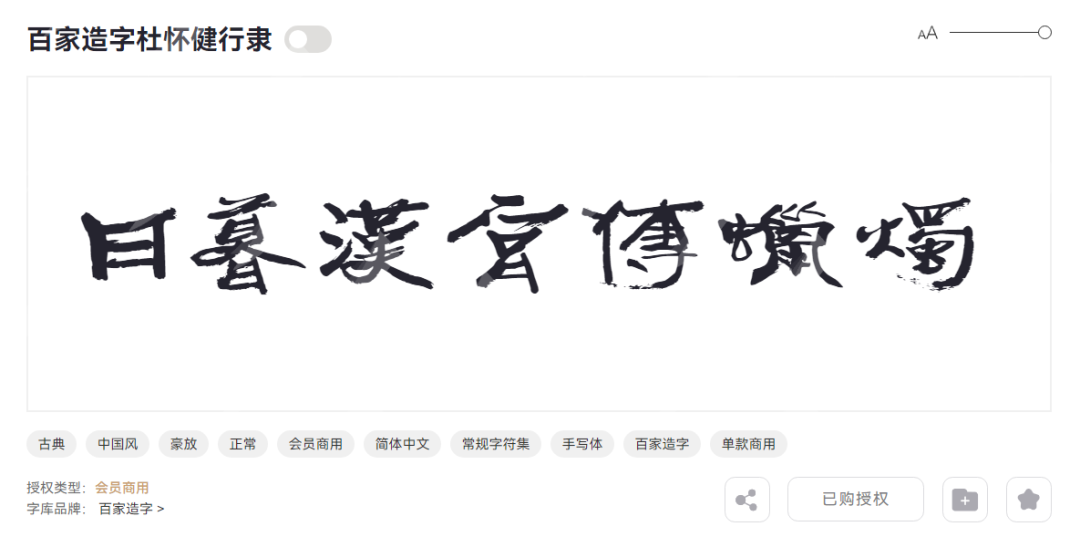
用来匹配《宁安如梦》的海外版海报,顿时宿命感、复杂感都有了。
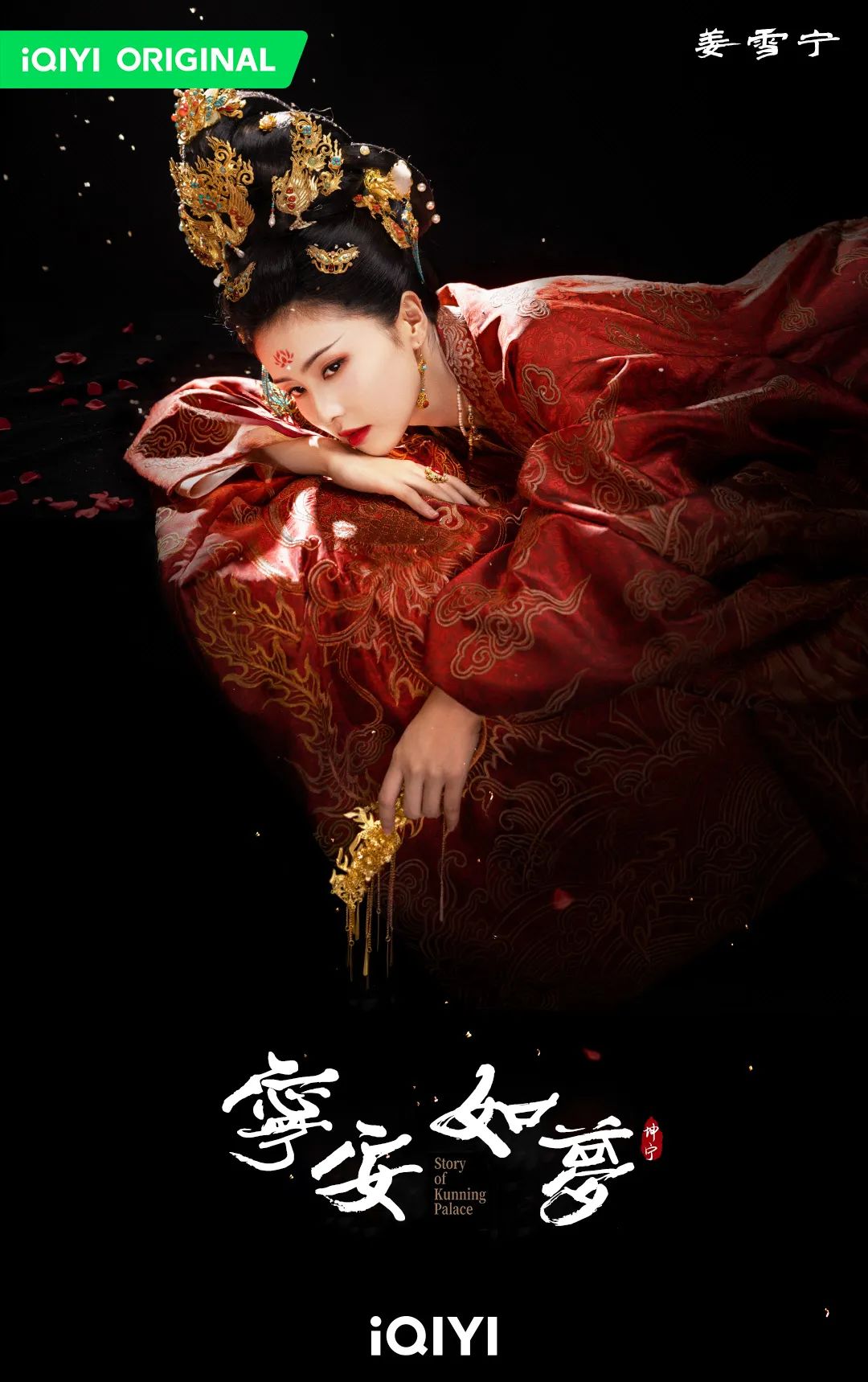
另外一款,百家造字知宥体,也是柚子很喜欢的字体,非常有故事感。
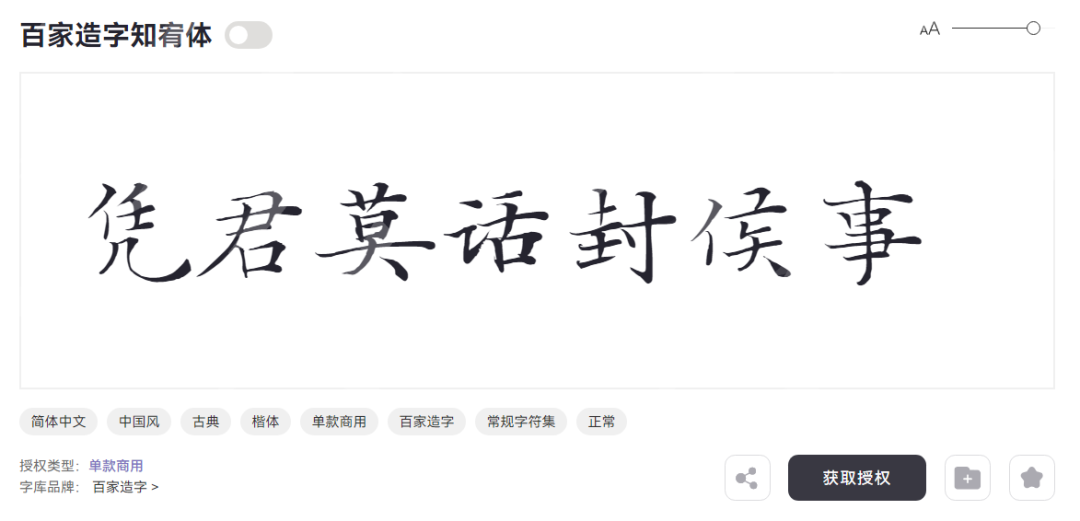
比较适合那句最出圈的台词,“苦果亦是果”,隐忍中又带些强制。
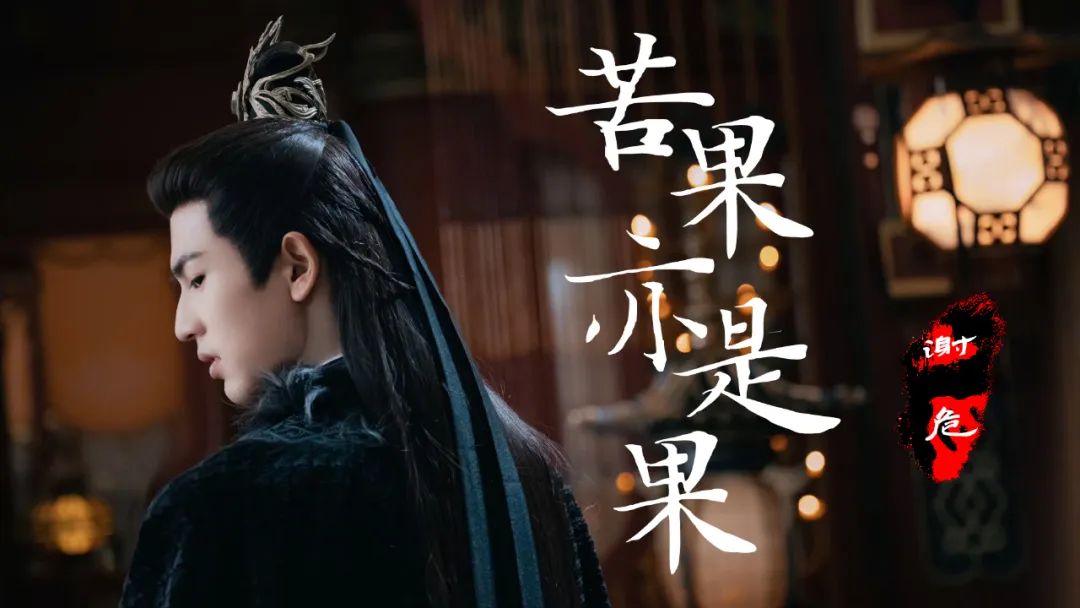
而清丽风雅的百家造字汲古楷书,没有一丝丝攻击性。
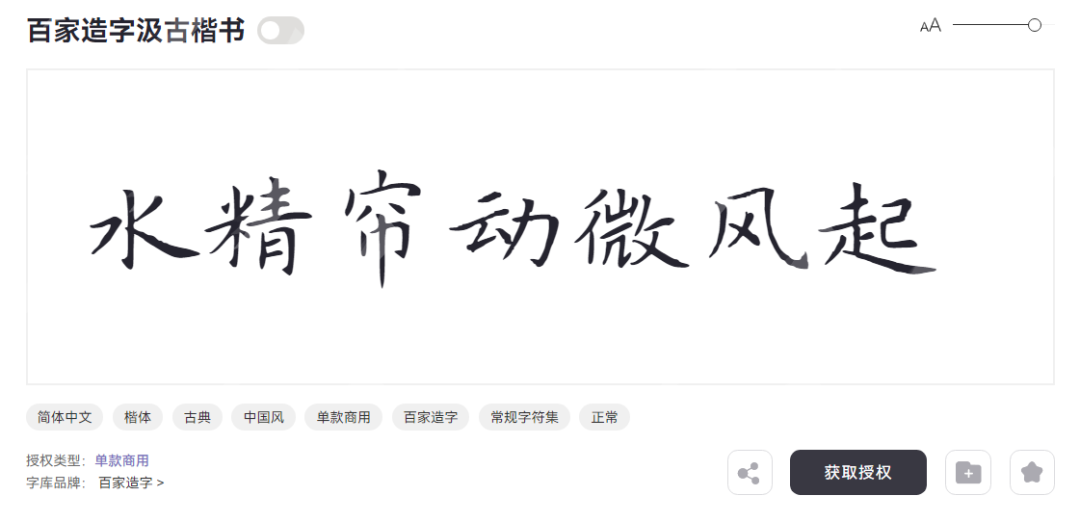
正好书写让“谢某无拘”,让姜雪宁以命换命的白月光——张遮。
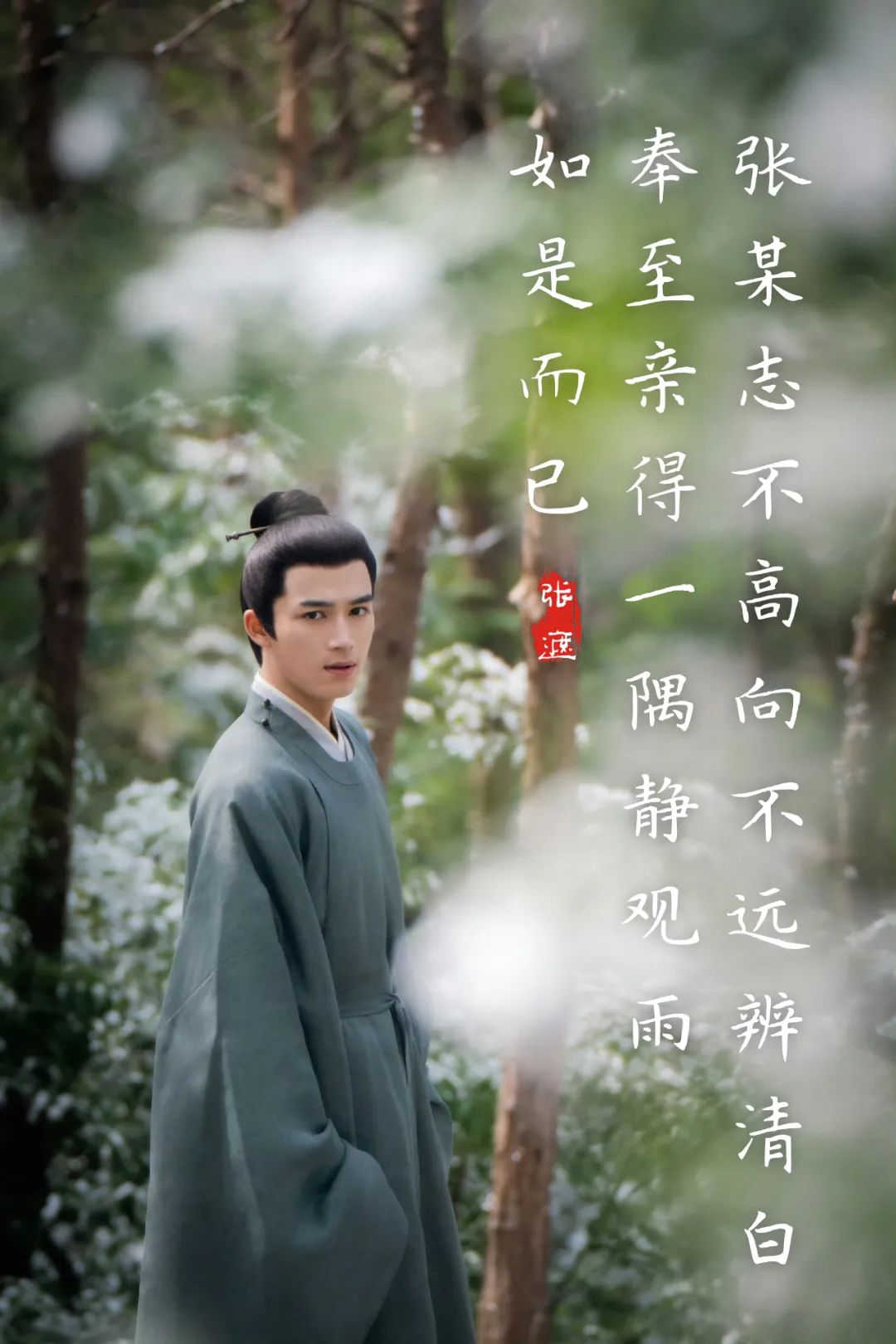
其实《宁安如梦》播到现在,大概可以用一句话来总结,那就是“一座宁安宫,两世荒唐梦”,而我选了百家造字小隶体,来展现女主的宿命论。
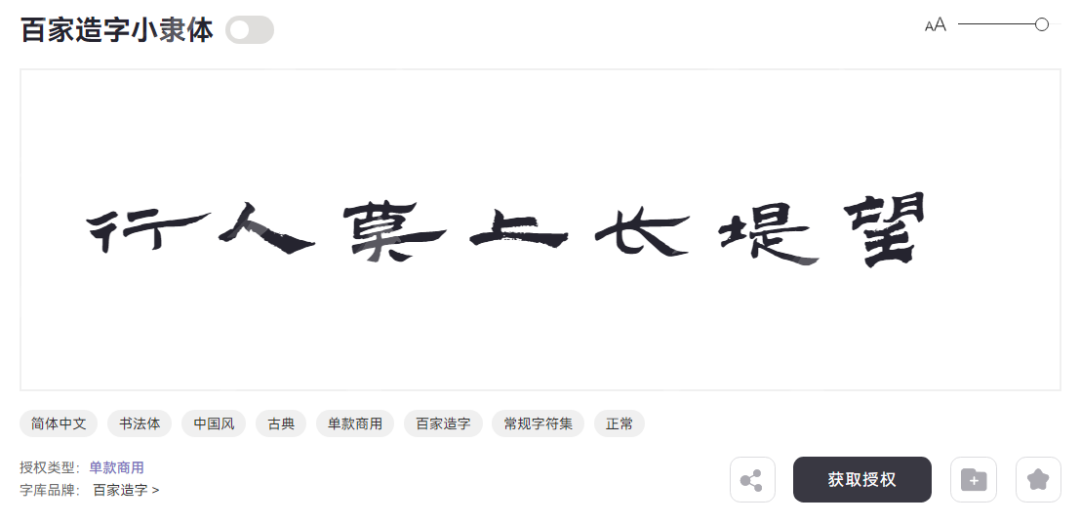
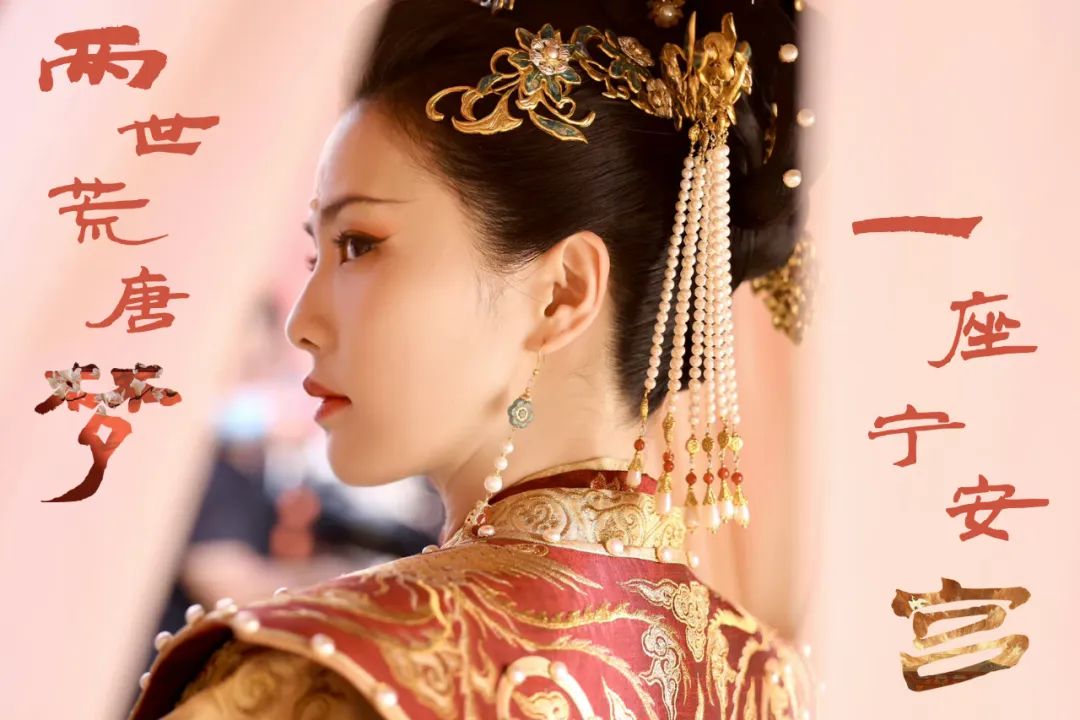
▲百家造字小隶体
▲百家造字知宥体